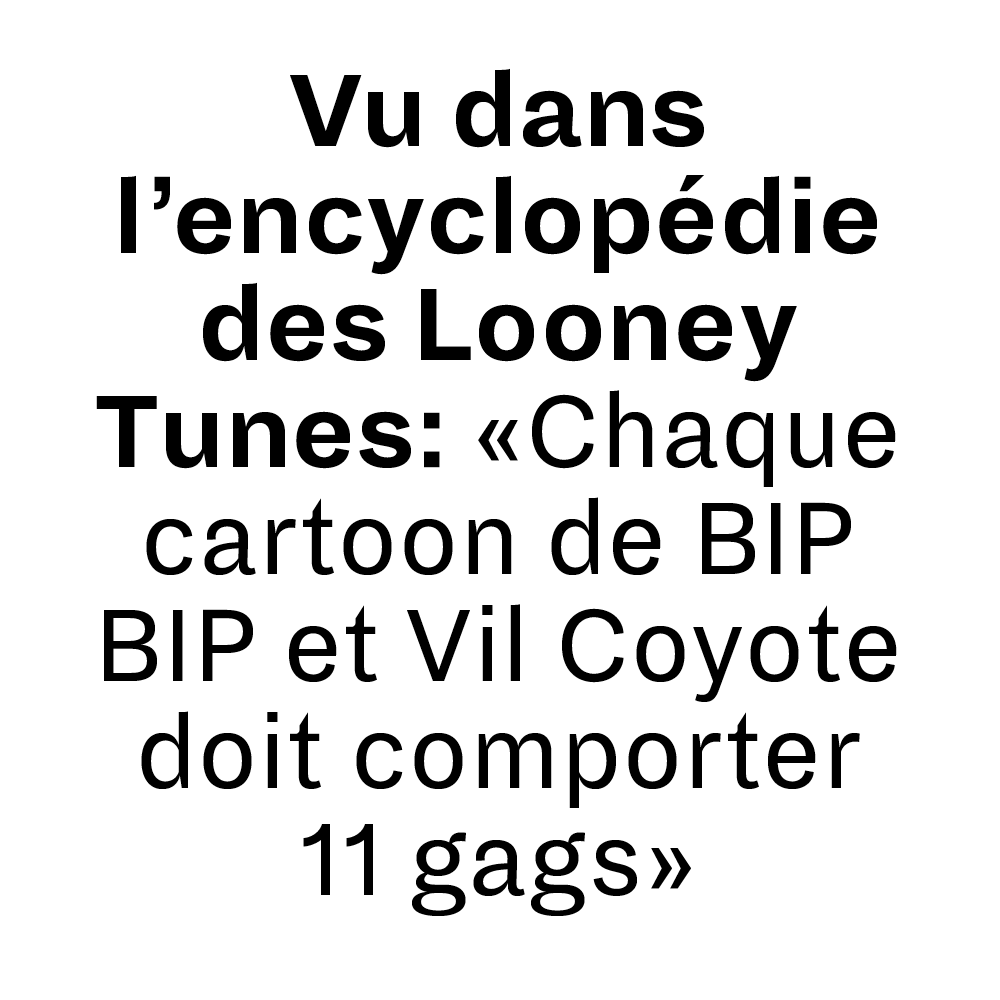
Schrift Empfehlungen gesucht (Sans Serif)
ich suche mal wieder eine Schrift und weil es mittlerweile soviele auch tolle, kleine Foundrys gibt verliert man selbst den Überblick. Hier kommt ihr ins Spiel. :) Habt ihr schöne Empfehlungen für eine Schrift, die so in Richtung "Dia" gehen? An der "Dia" interessiert mich vorallem der black-Schnitt, da bei diesem der Charakter der Schrift am besten hervortritt... also charakterstarke sans serif, erkennbarer Schreibduktus, dynamisch, irgendwie unperfekt... aber auch nicht zu rund so wie die Trivia zum Beispiel.
Ja, die meine ich!
Es wurde dann doch die Dia, hat dann doch am besten gepasst.